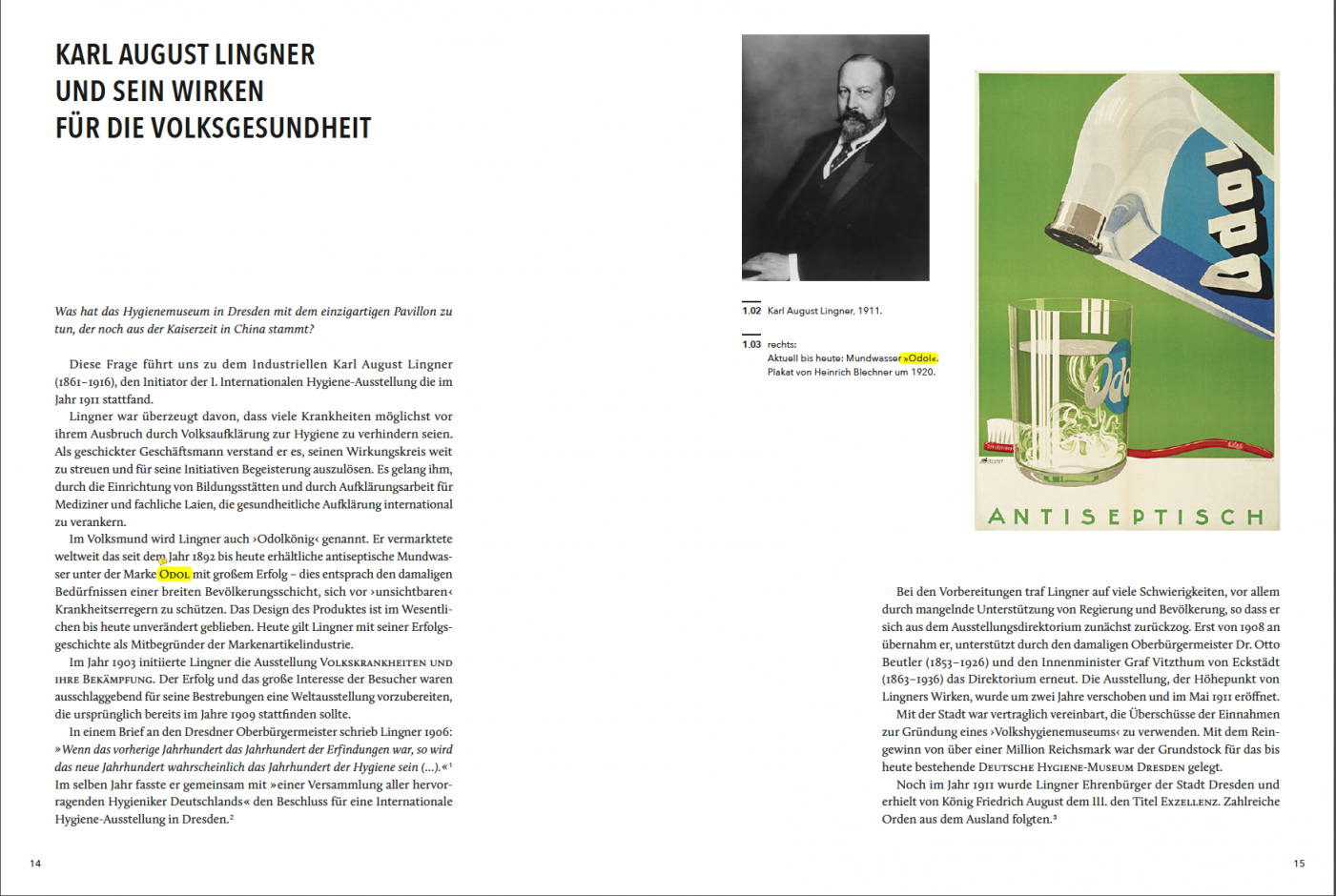
Mischung der Auszeichnungsformen
ich habe folgende Frage zum Thema Auszeichnungen in einer Publikation:
Im Fließtext gibt es eine Auszeichnungshierarchie:
Eigennamen in Kapitälchen, Zitate kursiv, und so weiter.
Muss diese Regel in den Bildunterschriften eine 1 zu 1 Entsprechung finden?
Also: Auch in den BUs Eigennamen als Kapitälchen?
Oder kann man hier auf Anführungszeichen zurück greifen?
Oder gar die Auszeichnung sein lassen?
Hintergrund ist der, dass die Schrift der Wahl für die Bildunterschriften keine Kapitälchen aufweist und ich zudem es unruhig finde, auch noch in den Bildunterschriften die Eigennamen auszuzeichnen.
Aus der Praxis heraus würde ich sagen, dass bei Bildunterschriften durchaus andere Regeln gelten können und dürfen. Diese sind ja «naturgemäß» erheblich kleiner gesetzt als der Haupttext, bald durchgehend kursiv, bald in einer anderen Schriftart (z.B. einer Serifenlosen im Kontrast zu Serifen im Lauftext).
Da muss man m.E. von Fall zu Fall entscheiden, wie weit man mit den Auszeichnungen gehen möchte. Ich hatte zum Beispiel schon Fälle, in denen alle Bildlegenden kursiv verlangt wurden – und Auszeichnungen in den Bildunterschriften hätten entsprechend recte gesetzt werden müssen. Das gab dann aber so ein unruhiges Bild, dass ich die Auszeichnungen in den Legenden in Anführungszeichen gesetzt habe. Ähnlich scheint es mir bei Deinem Fall: Kapitälchen in Bildunterschriften würde ich wohl auch zu vermeiden versuchen.
Es kommt aber halt, wie immer, auf das Gesamtkonzept an: Ich hatte jetzt eher knappe Bildhinweise im Kopf. Es gibt aber Fälle, bei denen bewusst kleine Texte zu Bildern stehen, in ganzen Sätzen – da würde ich eine Angleichung an die Vorgaben im Haupttext eher sehen.
Das bestätigt soweit erst mal die Hoffnung, dass man beim Setzen in Anführungen nichts »falsch« macht.
Ob man auch auf eben diese Anführungen verzichten könnte, muss dann wohl eher der Autor sagen.
Im Prinzip hattest du deine Frage ja schon in deinem Ursprungsbeitrag beantwortet. Wer auch immer die »Regel« (für diese Publikation) aufgestellt hat, dass Bildunterschriften in einer anderen Schrift gesetzt werden dürfen/müssen, kann genauso gut eine »Regel« aufstellen, was die Auszeichnung in Bildunterschriften bzw. anderem Text angeht.
Davon abgesehen kann es oft hilfreich sein, dasselbe Schriftattribut in verschiedenen Kontexten nicht unterschiedlich zu belegen. Wenn Kursivschrift im Fließtext also Zitate anzeigt, kann es verwirrend sein, Kursivschrift in Bildunterschriften anders zu verwenden. Aber wenn die Vorgaben nun mal so sind, muss man sich eben anders behelfen.
Die Gestaltung von Bildunterschriften ist ja sehr abhängig von der Art der Publikation. Im Magazin und der Zeitung sind sie wichtiger Leseeinstieg, da würde ich grundsätzlich auf weitere Unterscheidungen in den Auszeichnungen verzichten. Zudem sind Bildunterschriften dort meistens ergänzend, ihr Inhalt wiederholt meist Passagen aus dem Text in ähnlicher Form.
Bei Fachtexten sieht das manchmal anders aus.
Um was handelt es sich denn?
Es ist eine Publikation zur Geschichte – eher populär-wissenschaftlich, also ein Text für jedermann.
Jedoch mit vielen Auszeichnungsebenen, daher die Verwirrung.
Tatsächlich finde ich es immer noch unlogisch die Auszeichnungsformen innerhalb der Publikation zu wechseln.
Aber wenn es konsequent durchgezogen ist und an vielen Stellen wieder auftaucht, dann versteht der Leser, dass die verschiedenen Auszeichnungen im Fließtext zu einer Auszeichnung in den »begleitenden« Texten werden.
Dadurch wird der Satz ruhiger und schöner.
Zum besseren Verständnis hier ein Bild. Siehe zum Beispiel »Odol« im Text.
Eine unterschiedliche Darstellung in Form anderer Auszeichnung für die selbe Sache halte ich für schlecht. Entweder in der BU kommen die gleichen Auszeichnungen vor oder sie werden in der BU weggelassen. Odol müste unterm Bild nicht in Anführung stehen.
Noch mal grundsätzlich gefragt: Ist die Auszeichnungshierarchie für den Fließtext unumstößlich? Ich kann mich an keine Publikation erinnern, bei der ich die kursive Auszeichnung von Zitaten hilfreich für die Lektüre fand. So auch im gezeigten Beispiel. Wenn Zitate nicht kursiv gesetzt werden, kann die Kursive für Eigennamen etc. verwendet werden (die Kapitälchen finde ich vor allem für längere Namen ohnehin nicht optimal). Und schon hätte sich das Problem für Bildunterschriften erledigt, ohne bei der Lesefreundlichkeit insgesamt Einbußen hinnehmen zu müssen (oder, je nach Geschmack, sogar die Lesefreundlichkeit erhöht zu haben).
Das Layout steht fest und ist beschlossen ;-)